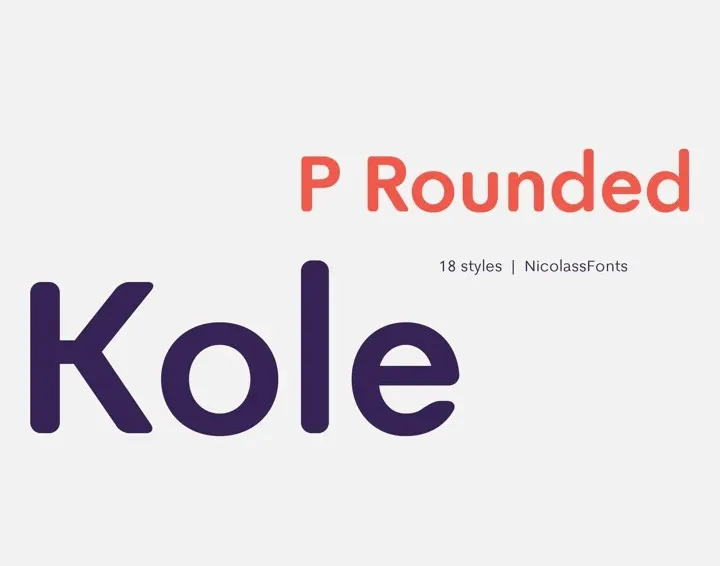
A fonte ‘Kole P Rounded’ é uma proposta interessante para designers que estão procurando por uma fonte sans-serif moderna e vibrante. Este conjunto completo inclui 18 pesos diferentes, criado para atender às necessidades de diversos formatos de mídia. Como sugere sua descrição original, Kole P Rounded se destaca como um excelente recurso para aplicações em estilos de marca, design editorial e design web. Seu design elegante com círculos arredondados faz dele uma opção perfeita tanto para títulos quanto para logos, garantindo um aspecto contemporâneo sem perder a fidelidade necessária. Kole P Rounded é especialmente indicado para aplicações visuais que desejam adicionar um toque de sofisticação e originalidade ao design. Suas linhas finas e leves complementam bem qualquer tipo de layout, garantindo uma aparência contemporânea que se adequa perfeitamente a uma variedade de contextos. Esta fonte é perfeita para ambientes onde há necessidade de transmitir um estilo moderno e vibrante, seja na propaganda, em embalagens ou no design editorial.